Marc Salinas (Barcelona, 1970) es todo un clásico en el mundo del diseño gráfico y la tipografía. Graduado en diseño gráfico por la Escola Massana y con una experiencia sobresaliente en el terreno laboral, queremos destacar aquí su faceta docente y divulgadora en la que la tipografía es la protagonista.
Marc, ¿Por qué decidiste especializarte en tipografía?
Recuerdo que siendo estudiante, descubrí en la biblioteca de la escuela un número de Emigre Magazine. Quedé totalmente fascinado por el trabajo de Zuzana Licko y su facilidad para diseñar fuentes customizadas que luego se aplicaban en esa revista. Sin darme cuenta y de forma progresiva fui reenfocando mis propuestas a piezas totalmente tipográficas más experimentales. Más adelante exploré el trabajo de diseñadores como Neville Brody o David Carson, piezas clave del postmodernismo gráfico y precursores de la tipografía digital. Gracias a ellos descubrí el editor de fuentes Fontographer y empecé a probar a diseñar mis propias tipografías. A partir de ahí tomé la decisión de que mi futuro profesional se centraría en lo que más me apasionaba del diseño gráfico; las letras.
¿Identificas en la actualidad alguna tendencia evidente en el uso de ciertos estilos tipográficos?
Centrándonos solo en tipografía, creo que hay una fuerte tendencia en el uso de fuentes lineales (sans serif) geométricas. Yo lo llamo el efecto “Post-Gotham”.
No creo que sea ni bueno ni malo. No me preocupa tanto la producción de este tipo de fuentes (que es mucha, por cierto) sino su uso indiscriminado.
Mi manera de entender la tipografía es básicamente formal, es decir, pienso que la forma de la letra debería ir en consonancia con el tipo de proyecto que se desarrolla y con su nivel de legibilidad según sus requerimientos técnicos y estéticos. Es cierto que el nivel de refinamiento en el diseño de fuentes está llegando a un punto que las hacen óptimas para un gran abanico de posibilidades, pero no todas sirven para todo.
¿Por qué es tan importante la Tipografía en el diseño? ¿Por qué es importante saberla aplicar?
La importancia de la tipografía en el diseño es evidente. No se puede diseñar sin tipografía pero sí se puede diseñar sólo con tipografía. Ejemplos como el trabajo de Josef Müller-Brockmann lo demuestran. En esencia, el objetivo de la tipografía (tanto en su diseño como en su aplicación) ha sido siempre el mismo: intentar comunicar de una forma atractiva cualquier texto, independientemente de su nivel de lectura. Es evidente que no se debe usar la misma tipografía para poder leer un libro que para señalizar de forma eficaz un aeropuerto, pero sí que está claro que el objetivo siempre es exactamente el mismo; que el receptor entienda el mensaje de la forma más clara posible.
Considero esencial que el diseñador deba tener las competencias y conocimientos imprescindibles en la aplicación de la tipografía en cualquier proyecto gráfico profesional, aplicado tanto a medios corporativos, como a editoriales digitales o interactivos.
Hablando de la tipografía en dispositivos móviles ¿qué opinión te merecen las variable fonts?
Veo a las Variable Fonts como una evolución técnica de las tipografías OpenType. La revolución ya apareció en los 90 cuando Adobe presentó las fuentes Multiple Master, que fueron, a mi modo de ver, las precursoras de las Variable fonts, es decir, fuentes donde el usuario puede obtener un estilo en concreto de una tipografía partiendo de unos extremos o masters, según la cantidad de modelos que tenga la fuente previamente diseñados. Comercialmente por diversos motivos en su momento no funcionaron, pero ahora con los formatos digitales y el responsive design, tienen mucho más sentido que hace 25 años. Disponer de un amplio abanico de estilos en una fuente y que se puedan adaptar de forma flexible a cualquier formato, todo eso en un solo archivo OpenType, provocará que modifiquemos radicalmente la forma de usar la tipografía.
Creo que con el resurgimiento de este viejo/nuevo formato sumado a las nuevas tecnologías y a la programación, hará que podamos disfrutar en los próximos años de proyectos tipográficos realmente interesantes. Un claro ejemplo puede ser el trabajo que está realizando el equipo de Underware.
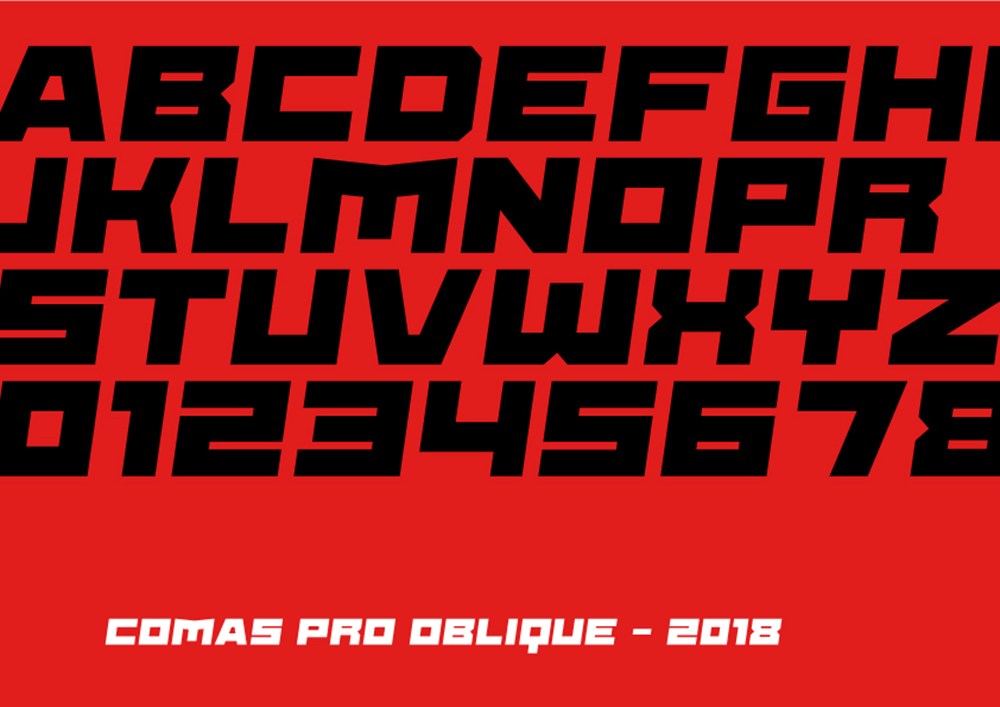
¿Veremos a cada usuario de estos dispositivos disponer de su propia tipografía personalizada?
Veo muy difícil responder a esta pregunta de forma taxativa, pero viendo la evolución tecnológica de la tipografía desde la aparición de los primeros formatos digitales respecto a toda la historia de la misma (solo 40 años frente a más de 500), los cambios que veremos en los próximos años seguro que serán asombrosos.
Si a partir de ahora tuvieras que trabajar solamente con tres tipografías, ¿con cuáles te quedarías?
Creo que es muy difícil responder a eso, así que en lugar de darte nombres te diré cualidades: escogería una serif moderna para poder usar en cuerpos pequeños y legible tanto para medios analógicos como digitales, una sans serif con carácter para trabajar los tamaños de letra más grandes y una que me pudiera hacer de puente entre estos dos grupos, para tener tres formas de letra totalmente diferente, como por ejemplo una slab serif. De hecho, podría tener todo esto buscando una sola superfamilia tipográfica que cumpliera todos estos requisitos, como la Nomada de Jordi Embodas. Vaya… ¡al final sí que se me ha escapado un nombre!
¿Cuáles son los objetivos de este Curso Online Experto en Tipografía Aplicada de LaBasad que tú diriges?
El enfoque es eminentemente práctico, ya que se trata de que el alumno adquiera el conocimiento imprescindible para que sepa aplicar la tipografía en cualquier proyecto gráfico profesional. Exploramos en detalle tres entornos que considero básicos a nivel empresarial: el corporativo, el editorial y el digital.